Hace poco más de una semana que "The Fast and the Furious 8" (si, si, ya van por la ocho) se ha estrenado en España con un reparto cargado de estrellas como Vin Diesel, Dwayne Johnson, Charlize Theron o Jason Statham. La primera de la saga tras el trágico fallecimiento de Paul Walker.
Como ya podrĂ©is imaginar, en Lettering Time nos hemos centrado mas en preguntarnos cual serĂa la tipografĂa que acompaña tantos años a esta saga de pelis de coches que en ver la pelĂcula ;)
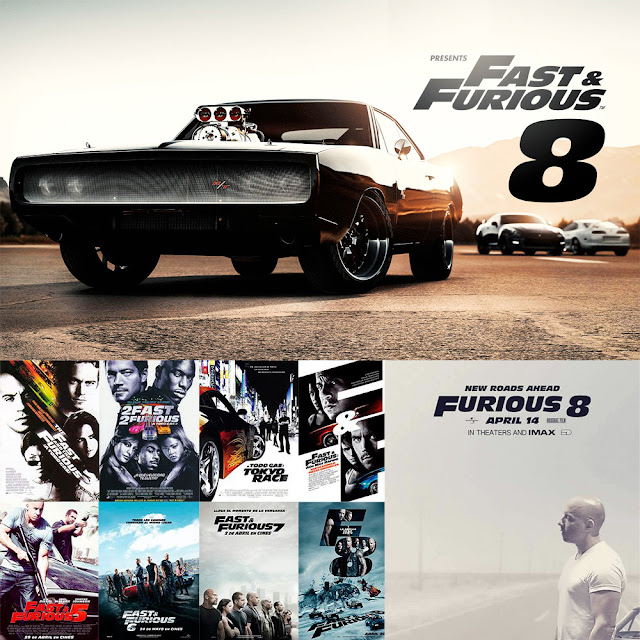
Si tu tambien te lo estabas planteando o lo estás pensando ahora mismo, tranquilo, vamos a sacarte de dudas.
En la saga "The Fast and the Furious" son fieles a su marca y su logotipo, puesto que a pesar de ir añadiendole diferentes efecto, degradados y cromados, han mantenido su tipografĂa a lo largo de las ocho entregas.
Aunque parezca mentira, ya ha llovido bastante desde que la tipografĂa utilizada en la saga "The Fast and the Furious" viera la luz, ya que fue diseñada por Roger Excoffon en la dĂ©cada de los 60. ¿Ya sabes de quĂ© tipografĂa estamos hablando? Pues bien, la tipografĂa usada en la saga mas famosa de pelis de coches molones no es otra que Antique Olive. Más concretamente, se trata de la versiĂłn "Nord Italic", que le aporta esa fuerza y velocidad perfecta para las 8 pelĂculas de "The Fast and the Furious".
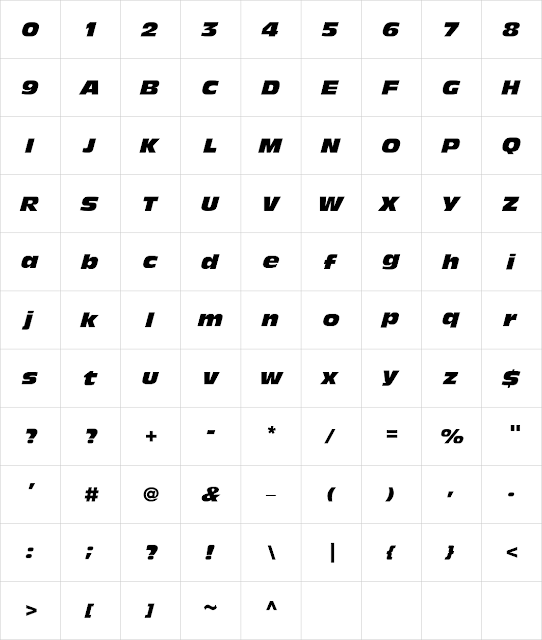
Si eres un fiel seguidor de esta famosa saga disfruta de la octava entrega y fijate en su tipografĂa al verla, y si no te gusta "The Fast and the Furious", incluso la odias, puedes consolarte con que en 2021, con la dĂ©cima entrega, se acaba la saga y con que te has llevado un frikidato tipográfico ;)